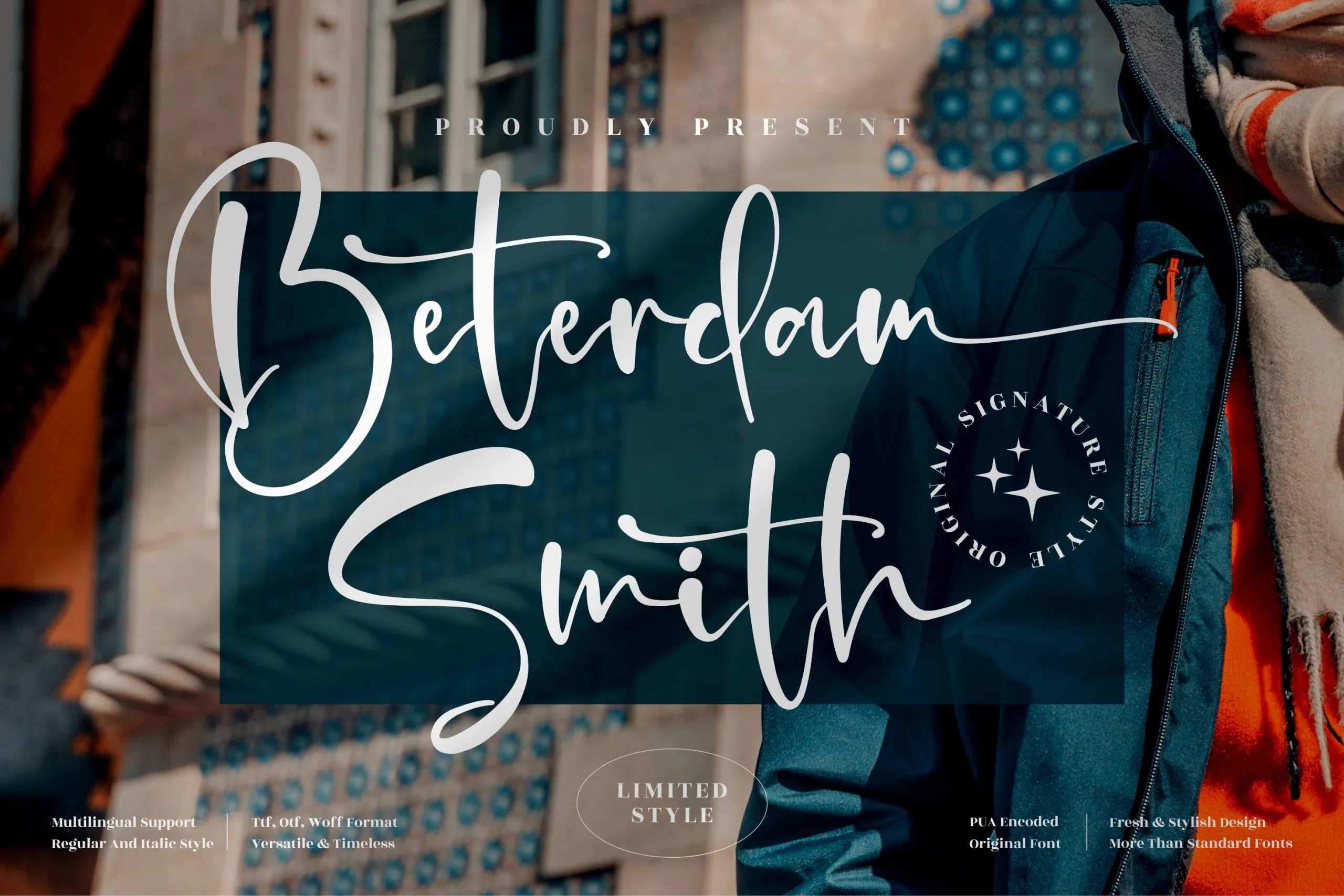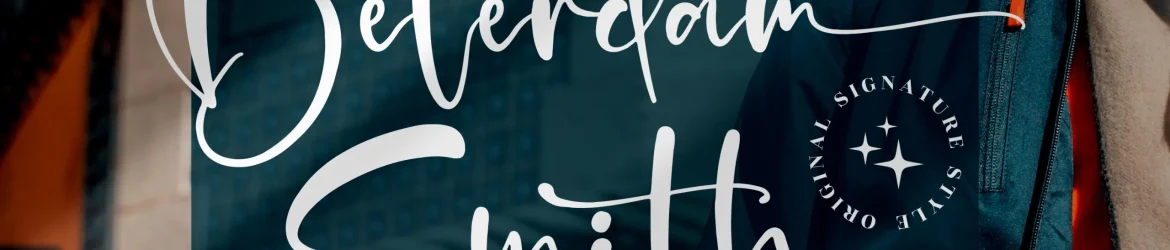
A Beterdam Smith Font é uma elegante assinatura fonte que traz aos projetos uma riqueza estilizada devido ao seu designer da Perspectype Studio. Esta fonte premium é perfeita para um vasto leque de aplicabilidades, incluindo logotipos, marcas de marca, design de mobiliário, embalagens de produtos, tigelas, frases, posters, sacolas de viagem, camisetas, capas de livros, cartões de nome, convites de casamento e aniversários, etiquetas, fotografia e até mesmo marcas de eventos especiais. Se estiver procurando por um toque de elegância em seu projeto, a Beterdam Smith Font é uma excelente opção para dar ao seu trabalho um acabamento único e luxuoso. Este estilo sofisticado não apenas adiciona valor aos seus projetos, mas também dá vida alesse visuais com um charme incomparável.